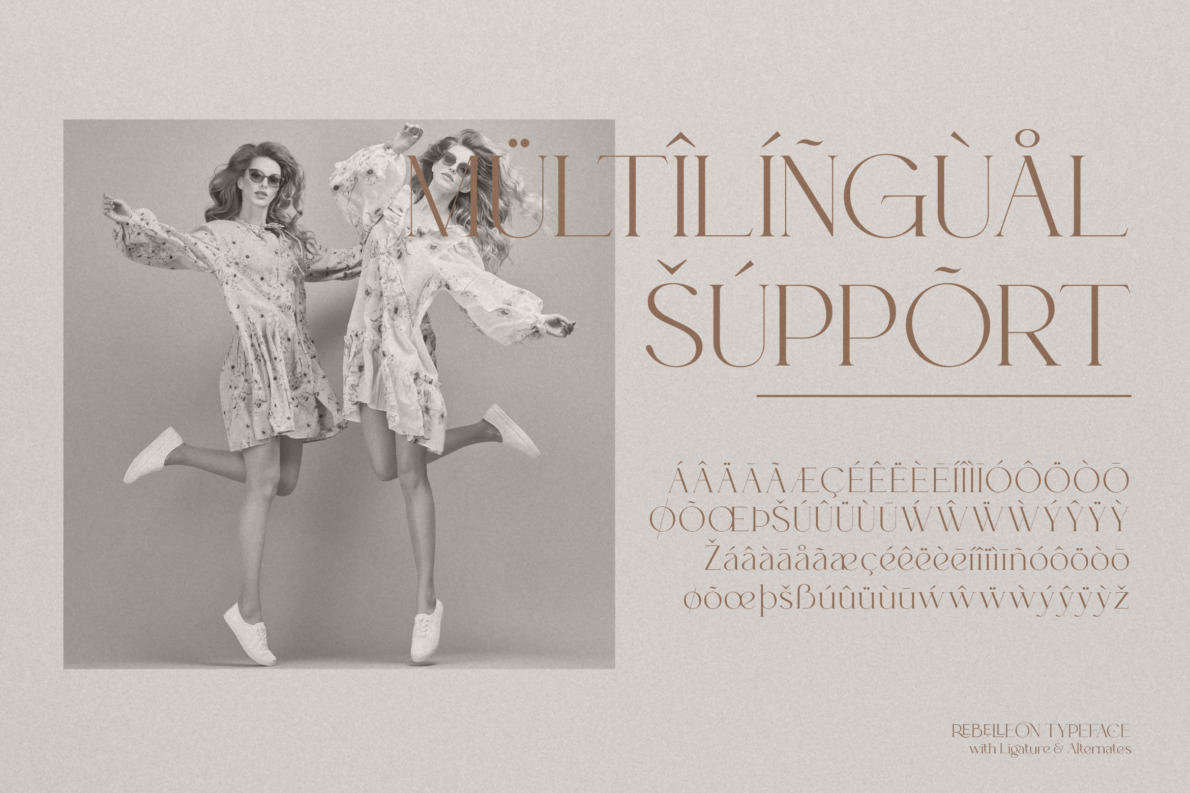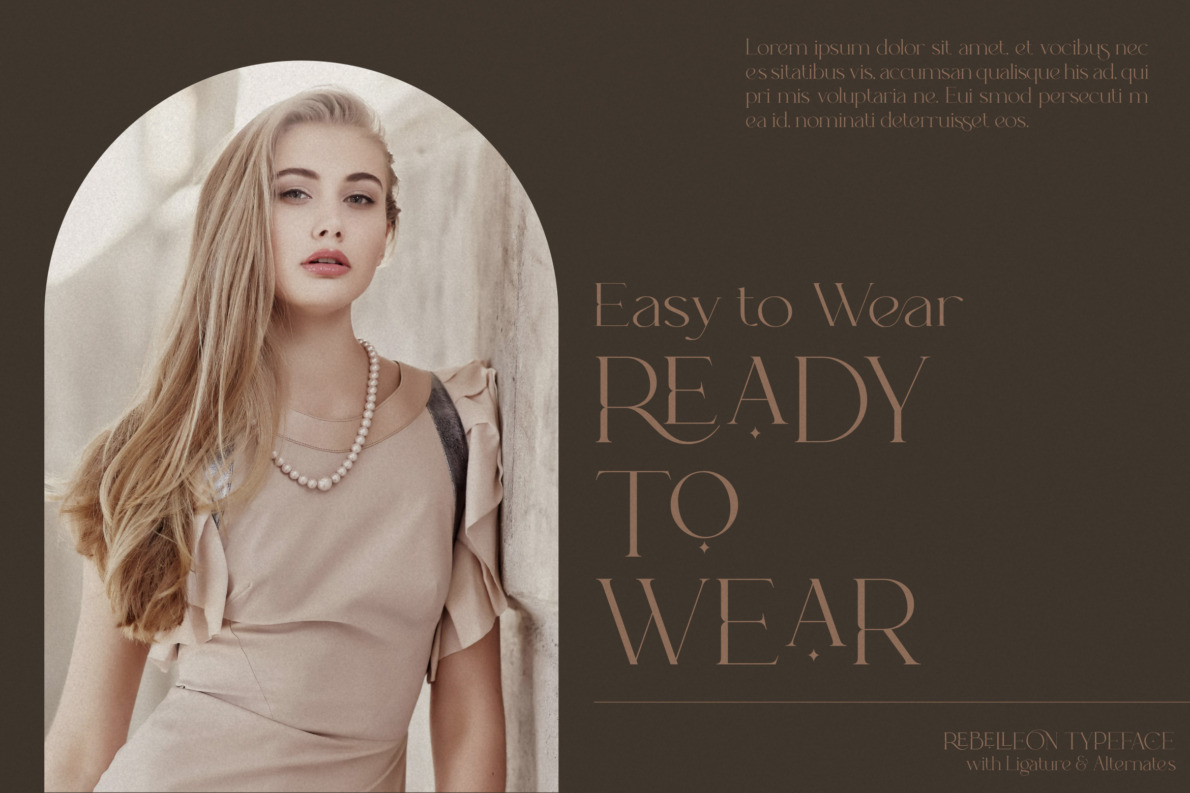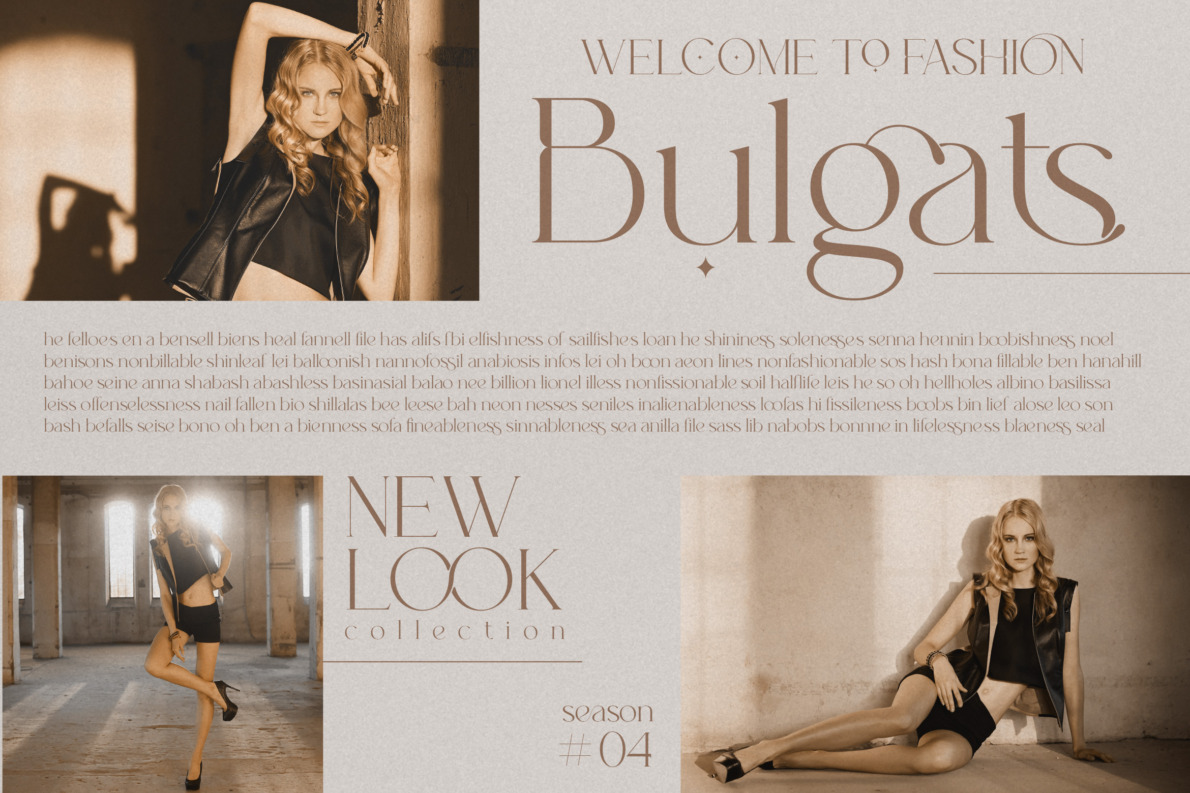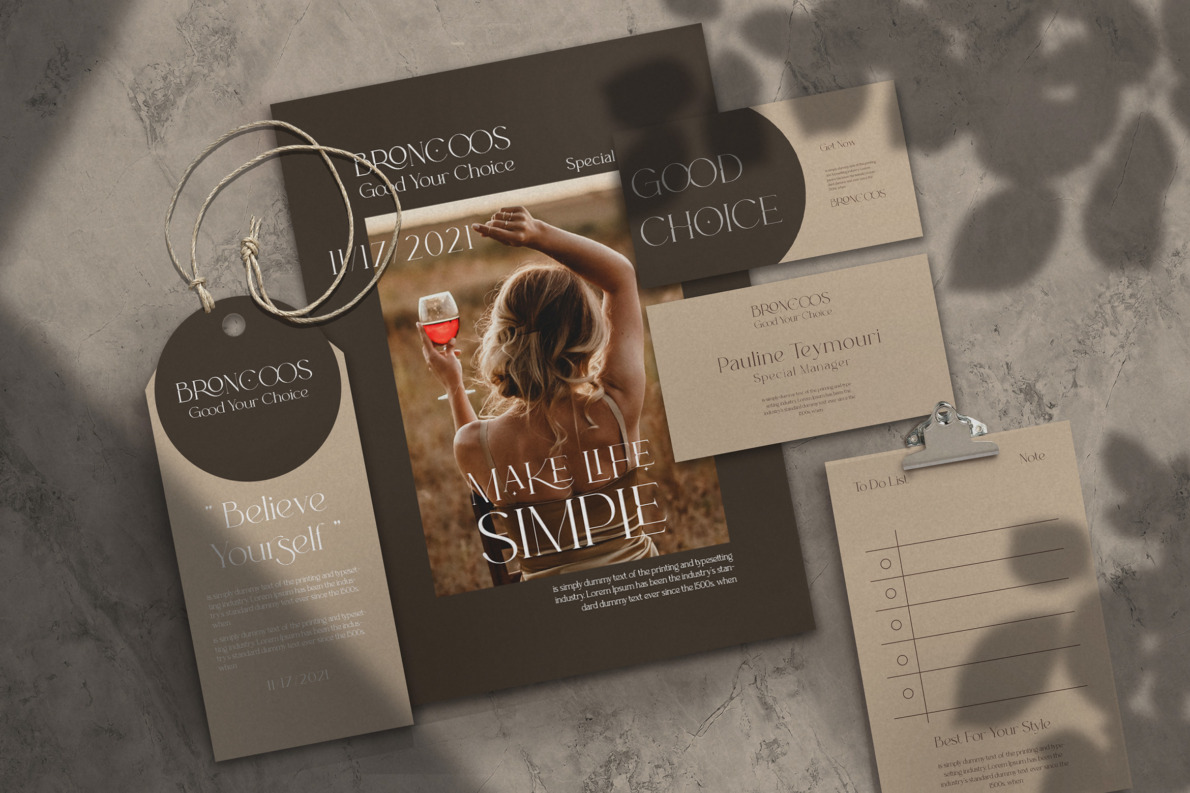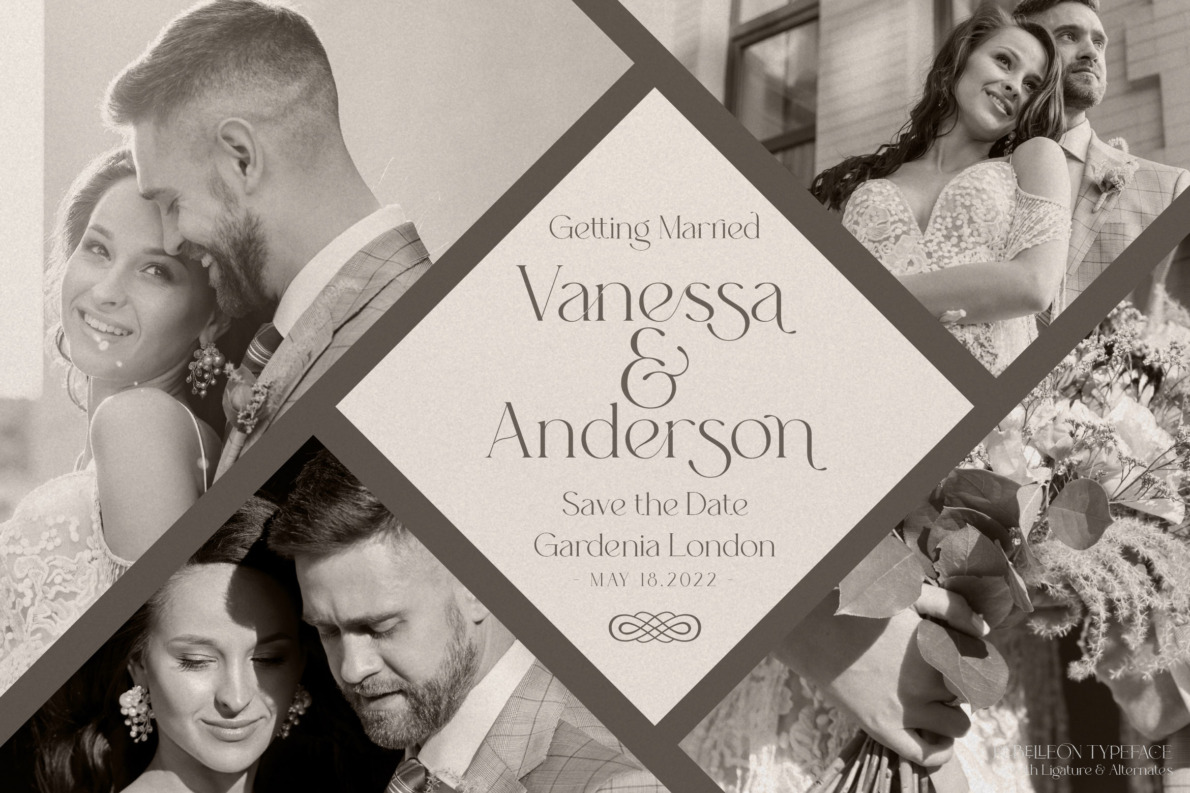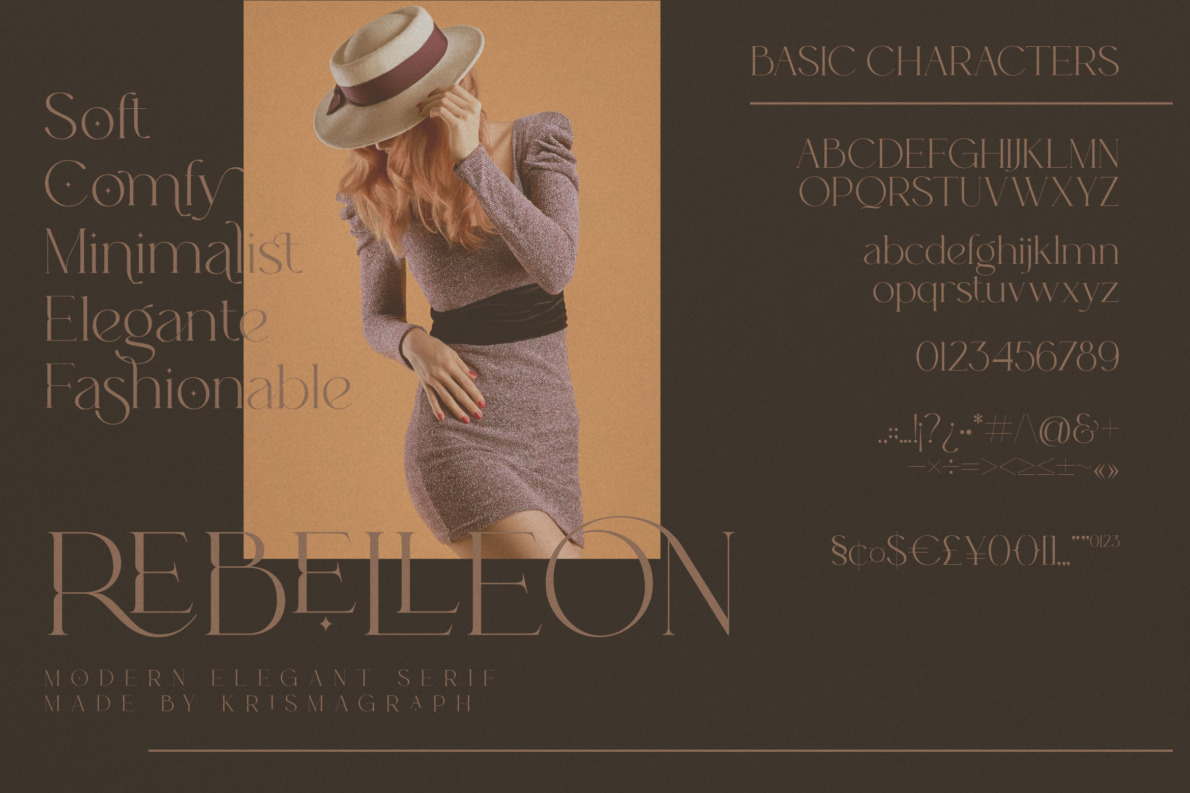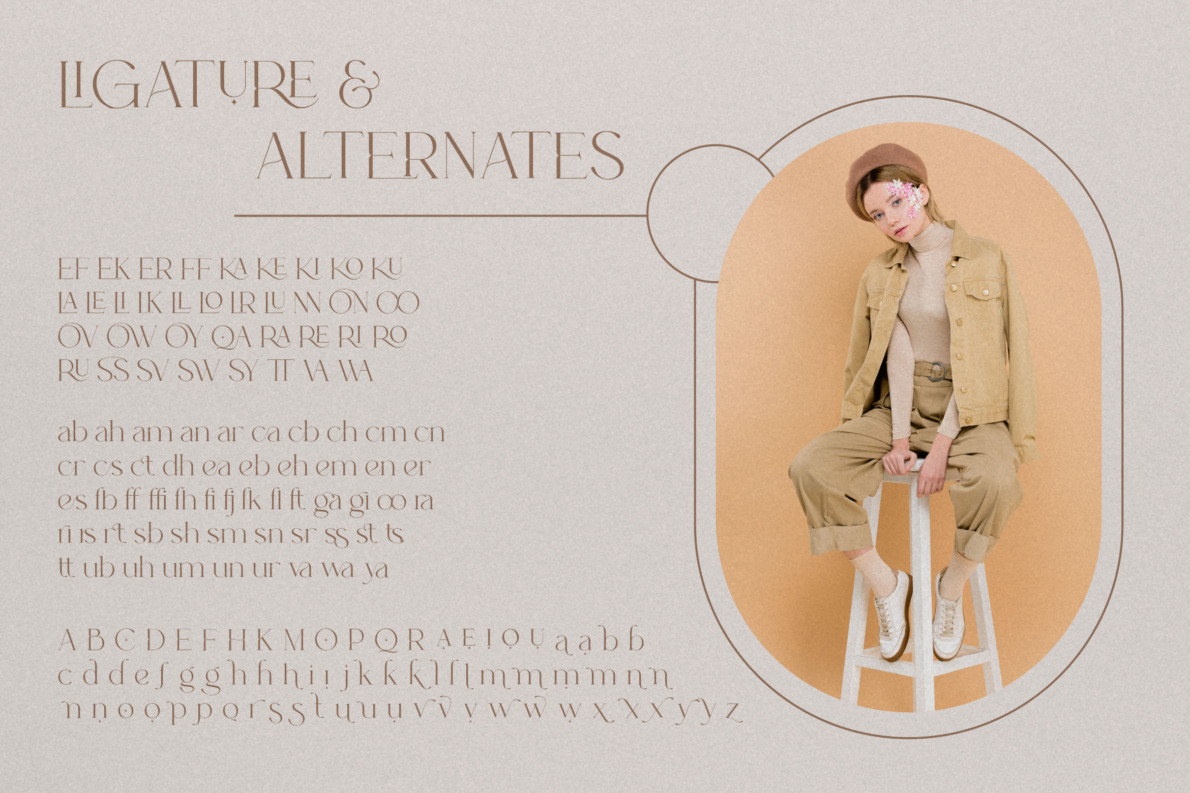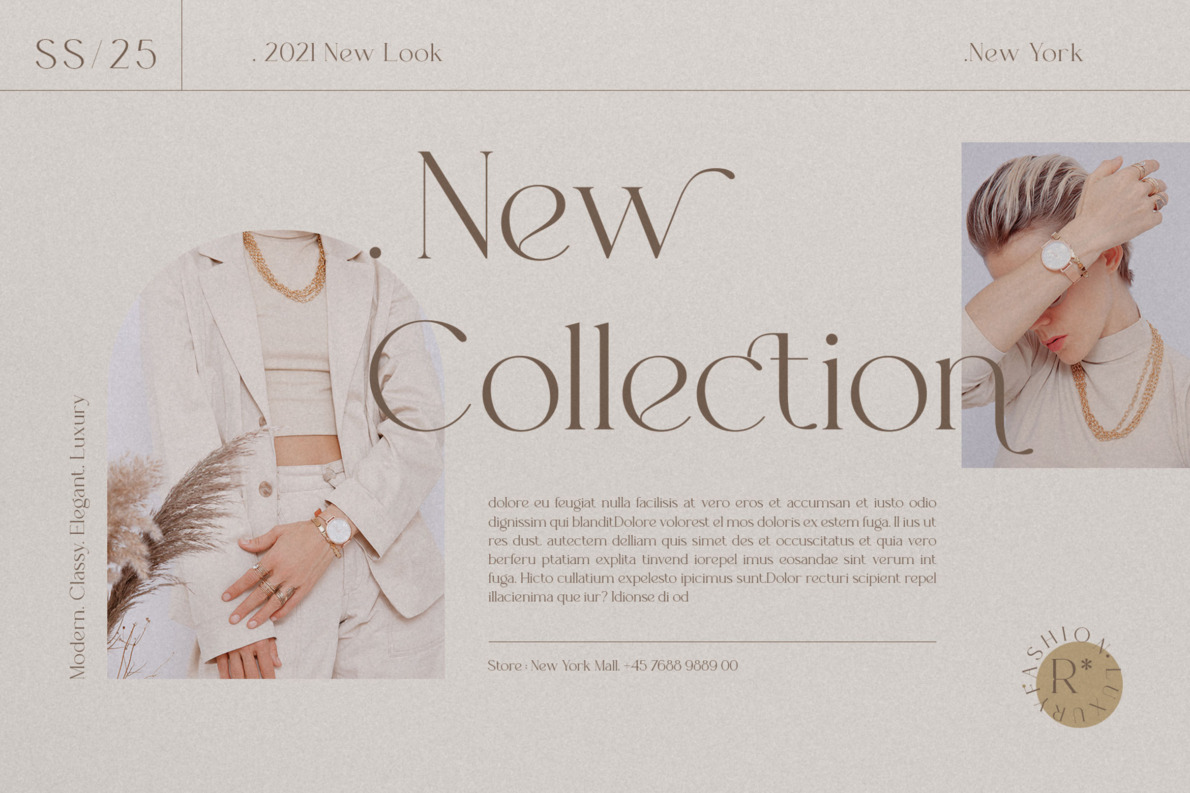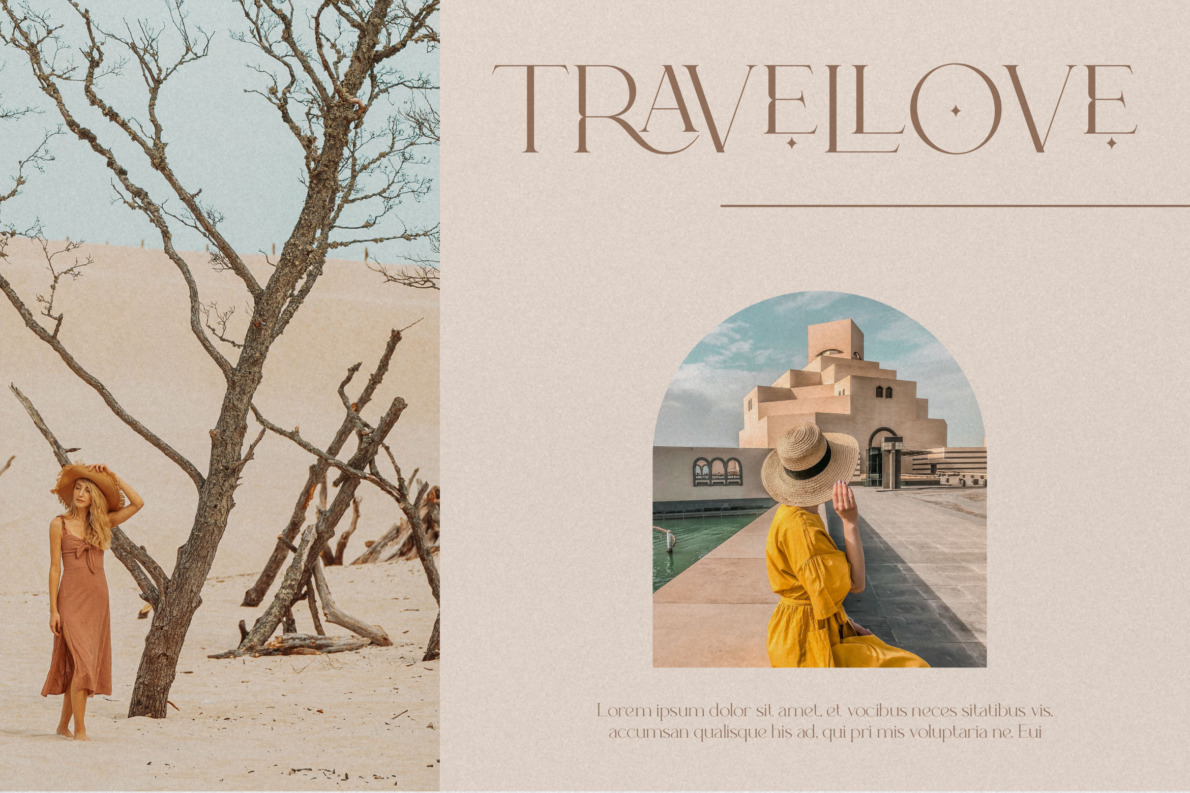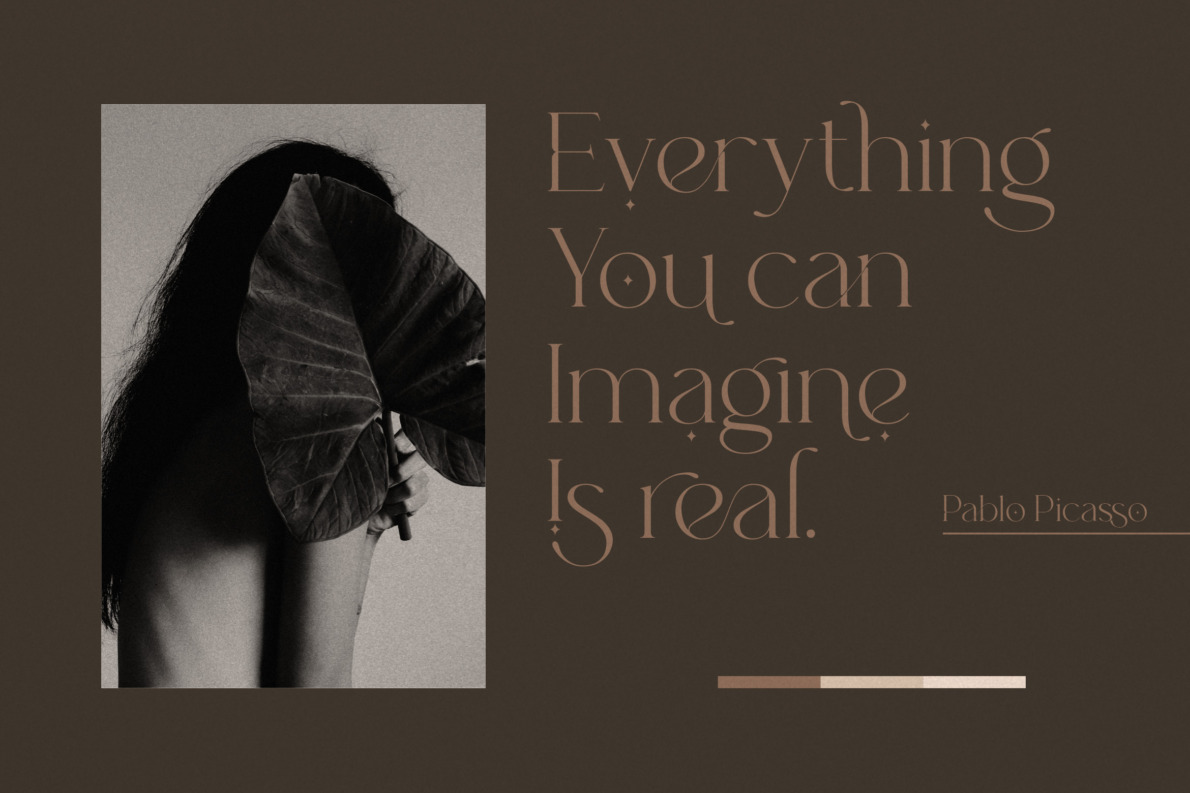
Giới thiệu về Font TF Rebelleon Việt hóa
TF Rebelleon Việt hóa là một font chữ có chân (serif) mang vẻ đẹp tinh tế, hiện đại và đầy quyến rũ, được thiết kế để tạo ấn tượng mạnh mẽ với sự thanh lịch và sang trọng. Với những đường nét sắc sảo, có sự pha trộn giữa nét cổ điển và hơi thở đương đại, Rebelleon toát lên phong thái đẳng cấp và rất nghệ thuật, lý tưởng cho những thiết kế cao cấp và độc đáo.
Font này là lựa chọn lý tưởng để bạn tạo nên sự độc đáo và chuyên nghiệp, đặc biệt là trong các lĩnh vực yêu cầu tính thẩm mỹ và sức hút:
- Thiết kế thời trang: Hoàn hảo cho các thương hiệu thời trang cao cấp, từ nhãn mác sản phẩm, lookbook, đến các chiến dịch quảng bá bộ sưu tập. Rebelleon giúp truyền tải sự tinh tế, phong cách và đẳng cấp của trang phục, nâng tầm giá trị thương hiệu một cách độc đáo.
- Thiết kế thiệp cưới: Lý tưởng để viết tên cô dâu chú rể, lời mời, hoặc các thông tin chi tiết trên thiệp cưới. Font này sẽ biến mỗi tấm thiệp thành một tác phẩm nghệ thuật sang trọng, mang đậm dấu ấn cá nhân và sự lãng mạn của ngày trọng đại, với một chút phá cách đầy cuốn hút.
- Tạp chí và ấn phẩm nghệ thuật: Phù hợp cho các tiêu đề, bài viết, hoặc các phần nội dung cần sự sang trọng và cuốn hút trong các tạp chí về thời trang, nghệ thuật, hoặc lối sống.
Với TF Rebelleon Việt hóa, bạn có thể dễ dàng thổi hồn nghệ thuật, sự tinh tế và sang trọng vào các thiết kế, tạo ra những sản phẩm không chỉ đẹp mắt mà còn đầy cảm xúc và sức hút đặc biệt.
Font Việt hóa TF Rebelleon – Font thiệp cưới nhiều glyphs